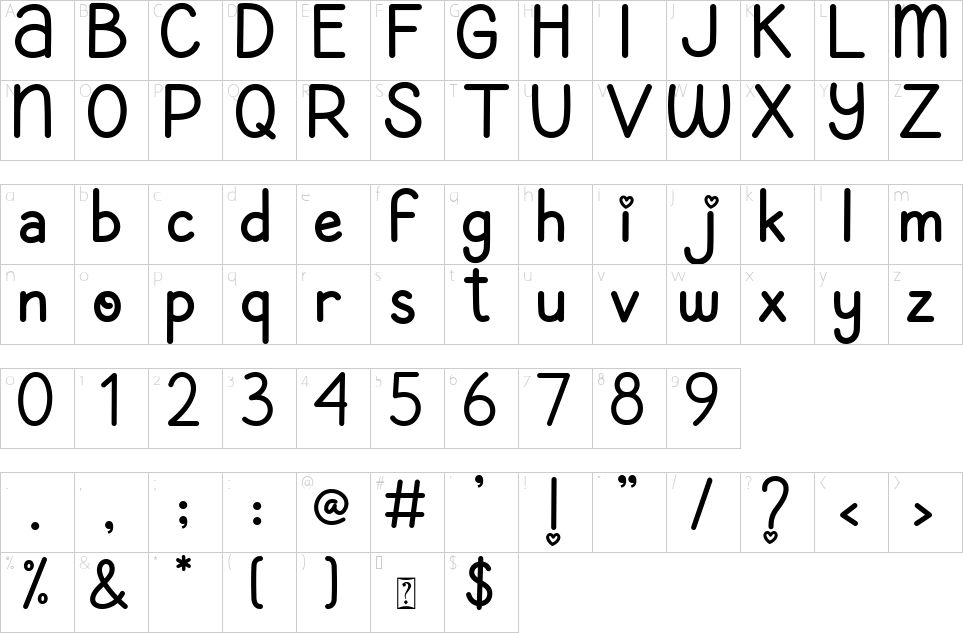
Descubra a delicadeza e a elegância da Amillova font, uma opção grátis para designers e amantes do design. Desenhada pela AEN Creative Studio, esta fonte oferece uma escolha versátil para qualquer projeto. Com 6,204 downloads, a Amillova é uma fonte confiável e popular, ideal para criar um design autêntico e sofisticado. Seja para aplicações de escritório, design gráfico ou criação de materiais digitais, a Amillova font é uma escolha atraente. Não perca esta oportunidade de adicionar uma peça única a seu portfólio ou projeto de design.